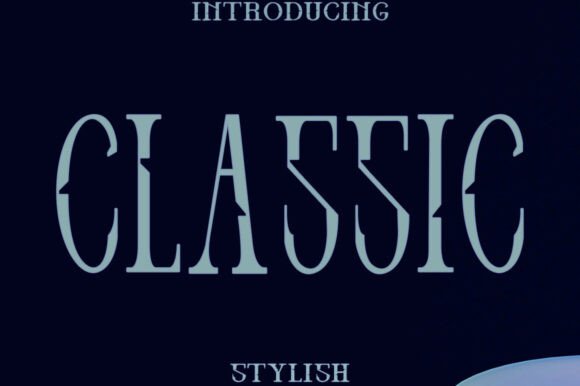
Classic
CLASSIC – La Police Serif qui Allie Élégance et Intemporalité
Vous cherchez une typographie qui incarne le raffinement tout en restant polyvalente ? La police CLASSIC répond à toutes les attentes des créatifs soucieux de qualité. Avec ses empattements soignés et ses courbes fluides, elle confère immédiatement une note d’exclusivité à vos projets.
Pourquoi choisir CLASSIC pour vos créations ?
- Design élégant et intemporel : les détails gras des lettres et les courbes harmonieuses donnent une impression de luxe classique.
- Lisibilité optimale : des caractères proportionnés et bien espacés assurent une lecture claire, même en petite taille.
- Adaptabilité exceptionnelle : idéale pour les logos, le branding haut de gamme, les éditoriaux, les invitations et les titres qui doivent se démarquer.
- Mix parfait avec les styles minimalistes et vintage : la combinaison d’éléments traditionnels et de touches modernes rend CLASSIC facile à associer à divers univers graphiques.
- Conviviale pour les designers : disponible en plusieurs poids, elle offre de la souplesse pour créer des hiérarchies visuelles cohérentes.
Utilisations recommandées
CLASSIC se prête particulièrement bien aux projets suivants :
- Logos de marques de luxe et de haute couture
- Identité visuelle d’hôtels, de restaurants gastronomiques ou de clubs privés
- Maquettes d’éditoriaux, magazines premium et livres d’art
- Invitations de mariages, galas et événements exclusifs
- Headers de sites web sophistiqués et de landing pages premium
Conclusion
En résumé, CLASSIC est la solution idéale pour tous ceux qui souhaitent allier tradition et modernité dans leurs projets graphiques. Son allure chic, sa lisibilité exceptionnelle et sa grande flexibilité en font un choix incontournable pour les designers qui visent l’excellence. Adoptez CLASSIC dès aujourd’hui et donnez à votre marque le prestige qu’elle mérite.